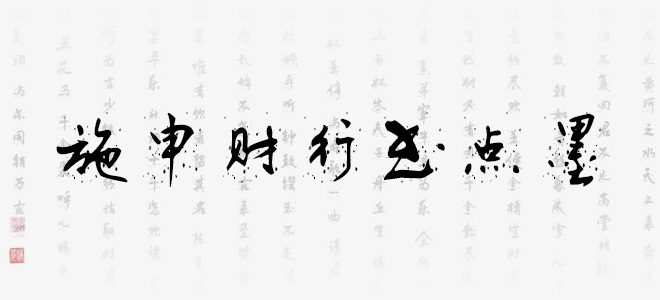
施申財(cái)行書點(diǎn)墨字體,在行書的基礎(chǔ)上增加的點(diǎn)墨背景特效,風(fēng)格鮮明,筆畫隨性,具有很好的視覺感,適合于文化類的宣傳設(shè)計(jì)、商業(yè)類品牌的廣告和產(chǎn)品包裝設(shè)計(jì)以及個(gè)性化文字排版等較多場景。
施申財(cái)行書點(diǎn)墨